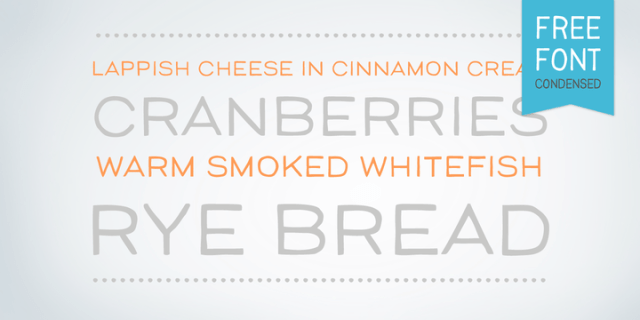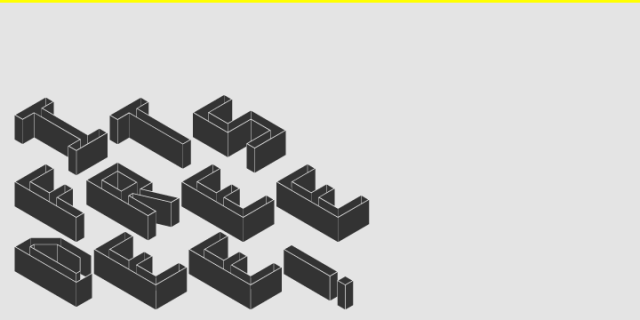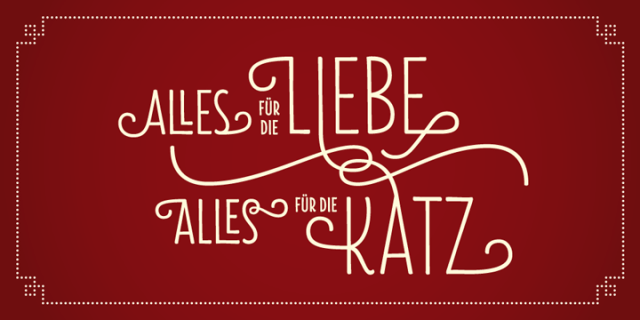
Os dejo un nuevo mini recopilatorio de tipografías. En este caso la fundición es My Font, una compañía muy prolífica y responsable de una app que seguro que todos conocéis, What the font, aplicación que te indica que tipografía es la que estás buscando para ese cliente que te da un jpg y te dice que te busques la vida. Aquí os dejo cinco tipografías muy cuidadas y con perfecto detalle que funcionan a la perfección. Para descargar las tipografías pulsad sobre la imagen y accederéis directamente a la página de descarga de la fundición. Espero que os guste y recordad que los like y los follow ayudan mucho así que visitadnos en Twitter y Facebook. También nos podéis encontrar en Flipboard buscando nuestra revista El Arquitecto de Ilusiones. Con cualquier duda que tengáis no dudéis en dejar un comentario!.